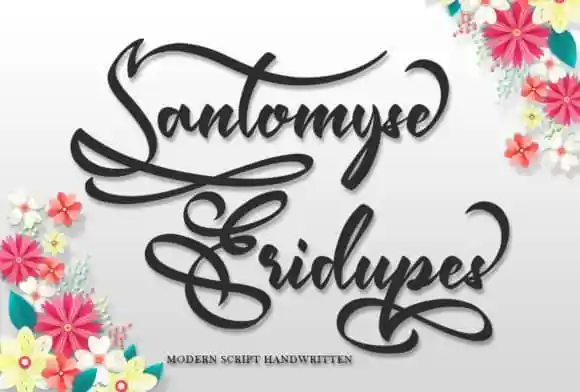
Santomyse Eridupes Script Font – Download Grátis
Santomyse Eridupes Script Font é uma elegante fonte moderna que mistura elementos da caligrafia com a leveza do traço humanoado. Criada pelo designer Sealoung, essa fonte transmite um equilíbrio perfeito e uma delicadeza impressionantes, fazendo das letras uma experiência visual refinada e envolvente. Com suas formas bem balanceadas, Santomyse Eridupes Script é uma escolha ideal para designers que buscam dar vida a suas melhores ideias criativas. Suas linhas fluídas e caracteres delicados permitem incorporar esta fonte em uma ampla gama de projetos, tornando-a um recurso indispensável para qualquer designer buscando adicionar um toque único ao seu trabalho.